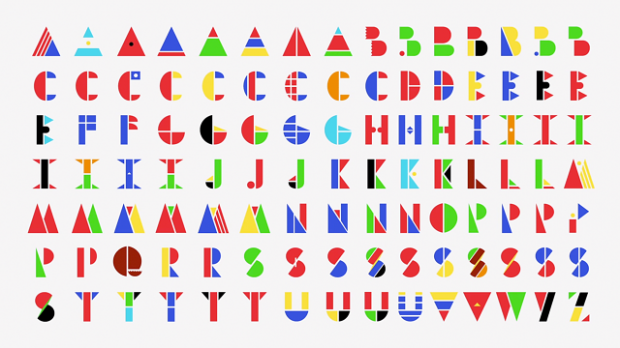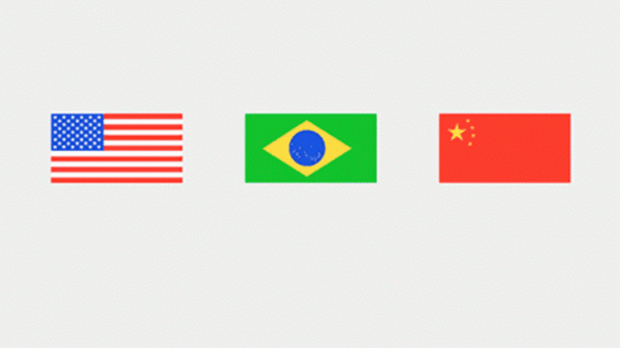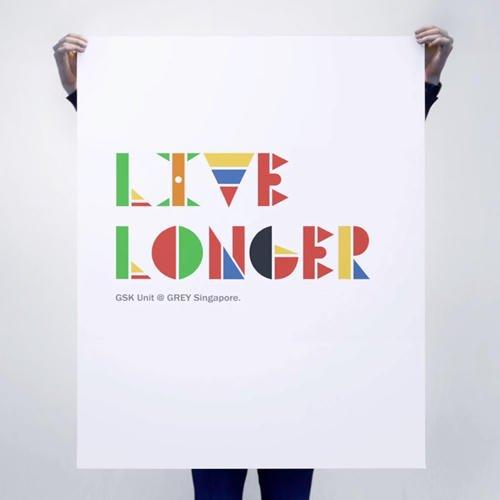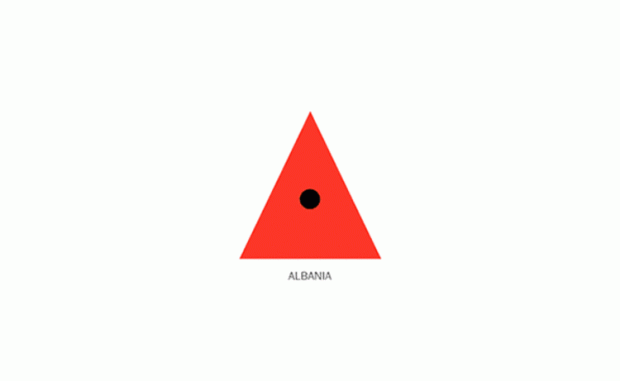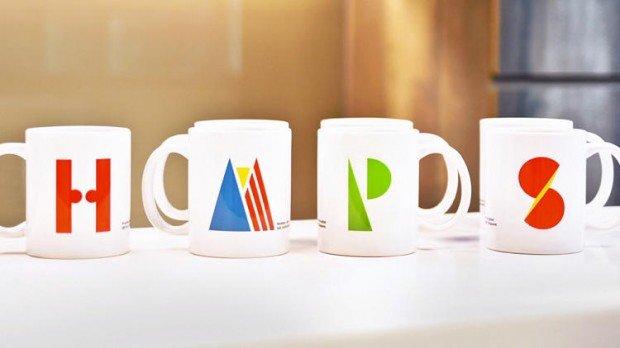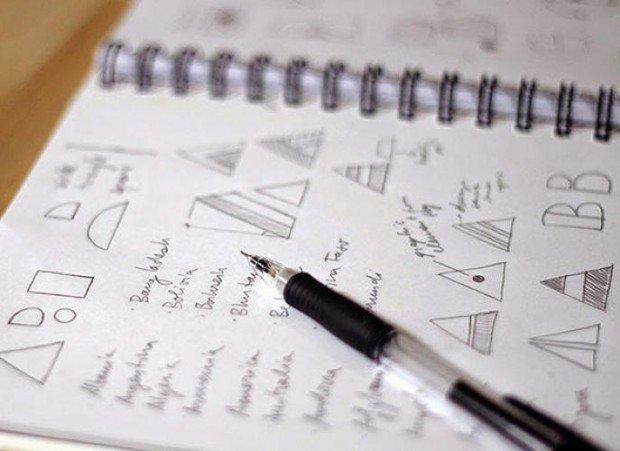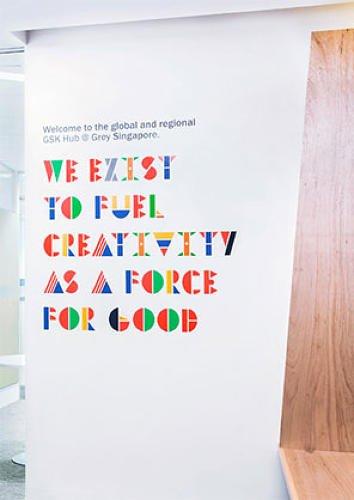
Multi-national typeface: le bandiere del mondo danno vita ad un font multiculturale
I prossimi mondiali di calcio che si terranno in Brasile sono ormai alle porte, per i creativi di tutto il mondo è tempo ormai di tirare fuori dal cassetto le bandiere e di utilizzarle per dare libero sfogo a progetti dai toni sempre più multiculturali.
L’agenzia Grey Singapore ha provato ad immaginare come le bandiere di ogni stato potessero dare vita ad un font ribattezzato multi-national typeface che supera ogni confine, dove ogni lettera dell’alfabeto – sono 106 in totale, perchè molti paesi hanno la stessa iniziale e perciò la lettera ricorre più volte – è realizzata trasformando la bandiera di ciascun paese nell’iniziale del nome dello stato, a partire dalla A della bandiera a stelle e strisce per finire con il verde, il nero e il dorato della bandiera dello Zimbawe che diventa una Z.
Questo incredibile progetto nasce dall’idea di riflettere la multiculturalità di un’agenzia che accoglie persone da ben 12 paesi del mondo con esperienze lavorative attraverso 49 nazioni e che è presente in ben 106 mercati.
Ecco alcune immagini ed un incredibile video che illustrano al meglio questo alfabeto creativo: